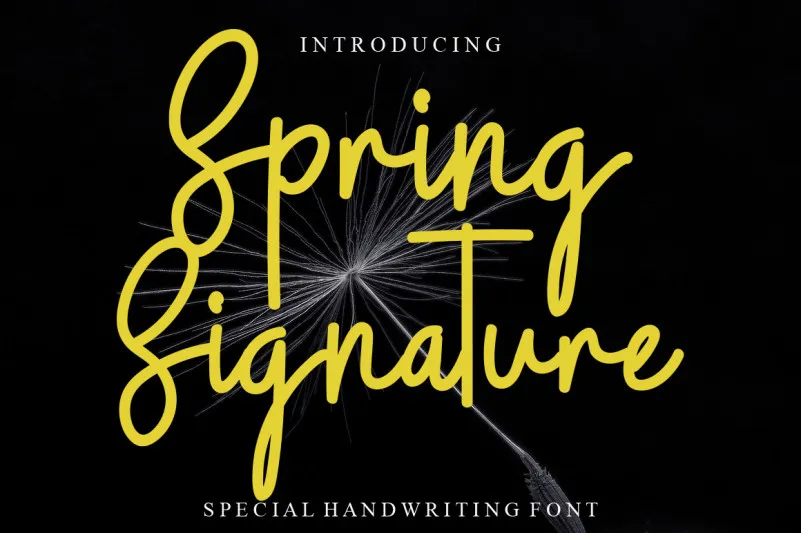
Spring Signature Font – Download Grátis
Esta é uma fonte escrita a mão genuína e cívica com um toque delicado e curvilíneo. Ela traz um toque leve e romântico a cada projeto que você criar, tornando-o naturalmente belo. Seja para cartões de aniversário, mensagens pessoais ou até mesmo gráficos digitais, essa fonte entrega uma sensação única de conforto e simplicidade. Feita pelo designer levincreative, o ‘Spring Signature Font’ é perfeito para quem busca um toque artesanal em seus projetos, mantendo-os ao mesmo tempo modernos e agradáveis aos olhos.